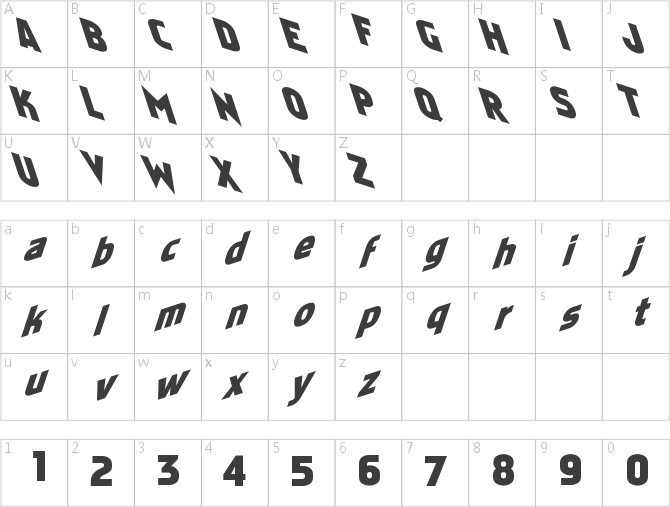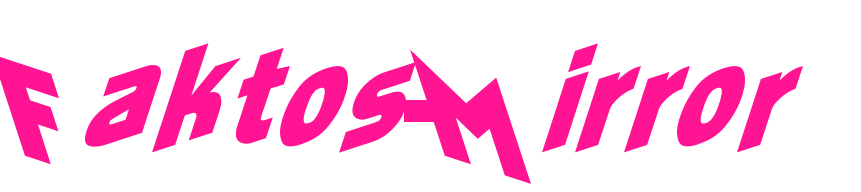
Faktos-Mirror 詳情頁(yè)
Faktos-Mirror字體字庫(kù)是一款讓人賞心悅目、百看不厭的英文字體,適合各類廣告和產(chǎn)品包裝設(shè)計(jì)應(yīng)用,字體大小0.05MB,格式為ttf字體,上傳用戶是昊天金誠(chéng),作者/版權(quán)方為未知